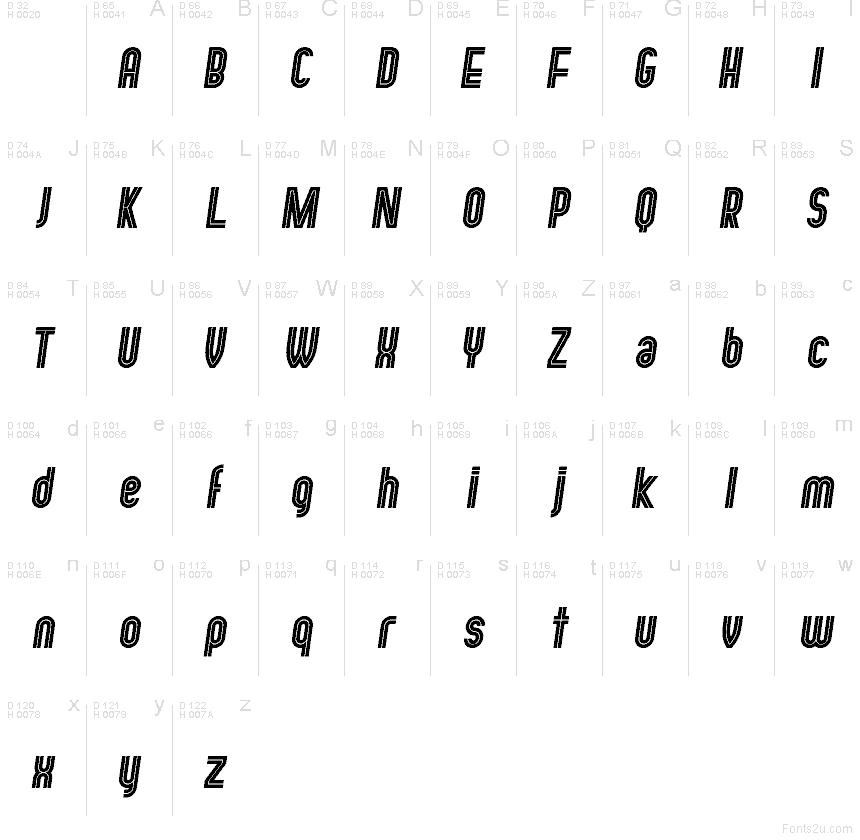
Die Schrift Hofmann Extravagant Italic von Vladimir Nikolic ist eine kostenlose Retro-Display-Schrift. Ihre schrägen, konturierten Buchstaben mit feinen Innenstreifen verleihen jedem Zeichen einen schichtartigen, posterartigen Look. Die abgerundeten Formen und die engen Abstände erzeugen einen beständigen Rhythmus, während der kursive Neigungswinkel dem Design eine dynamische Note verleiht, ohne gehetzt zu wirken.
Hofmann Extravagant Italic eignet sich hervorragend für Vintage-Poster, Logos, Albumcover, Beschilderungen und redaktionelle Titel, die eine stilisierte, aber kontrollierte Linienführung erfordern. Diese kostenlose Schrift ist zudem ideal für Verpackungen, Social-Media-Grafiken und kurze Werbetexte, bei denen die konturierte Gestaltung und der Retro-Stil das Layout allein tragen können.
Hofmann ist in den Schnitten Regular und Italic erhältlich.
Hofmann Extravagant